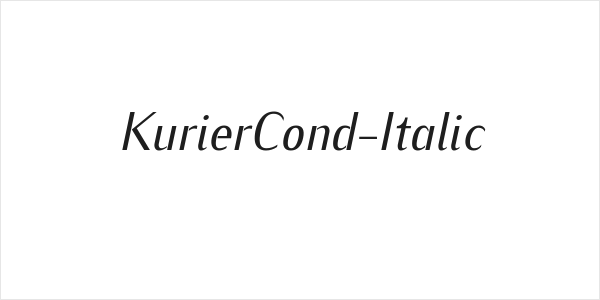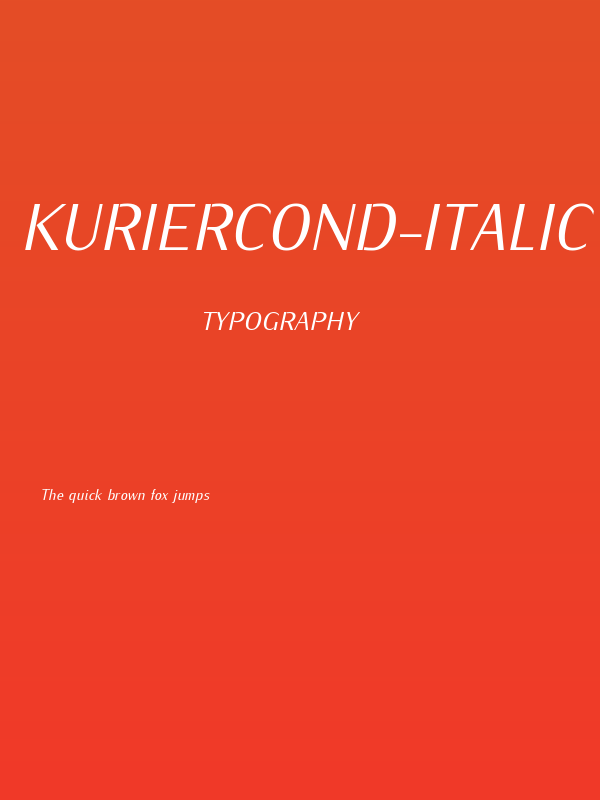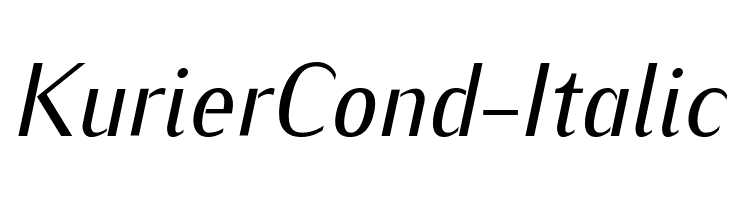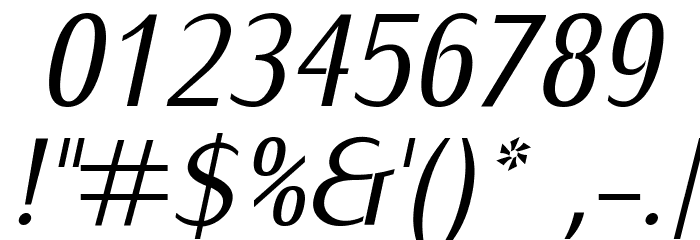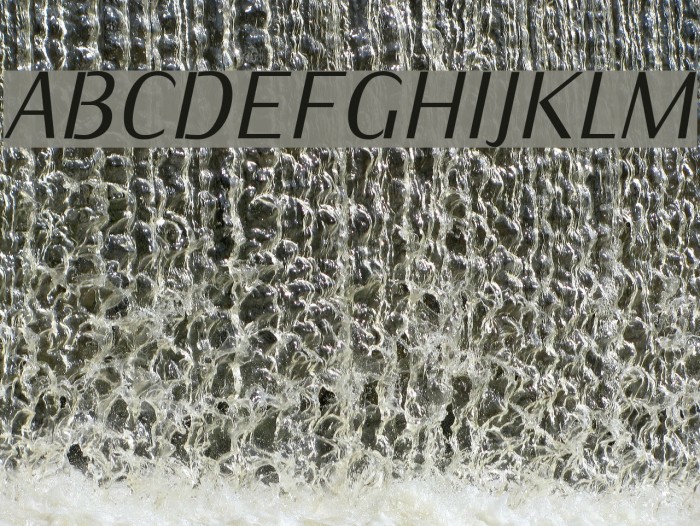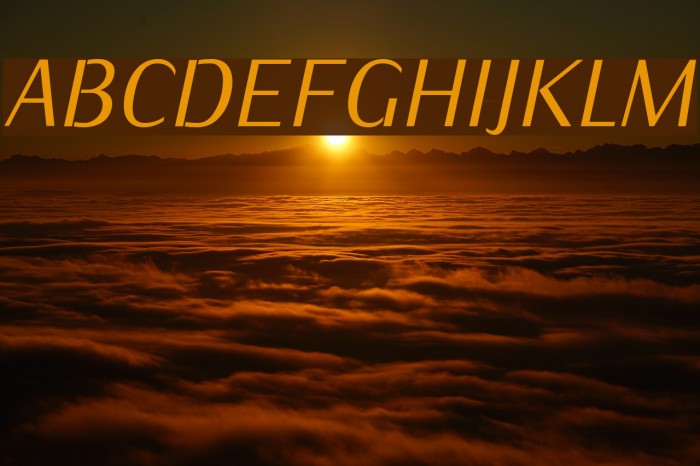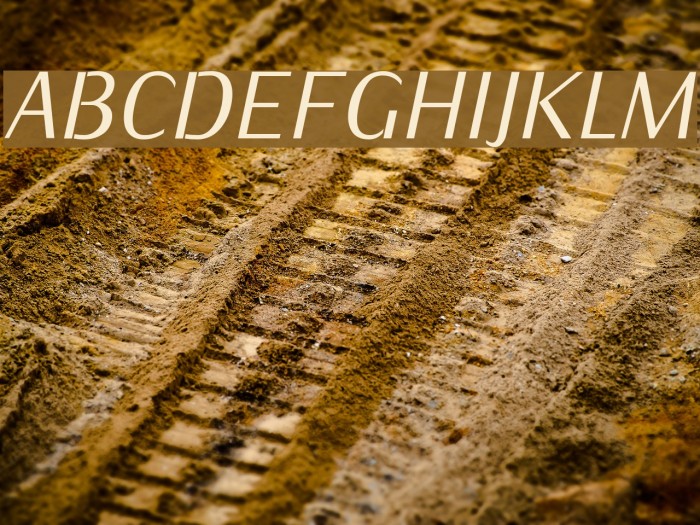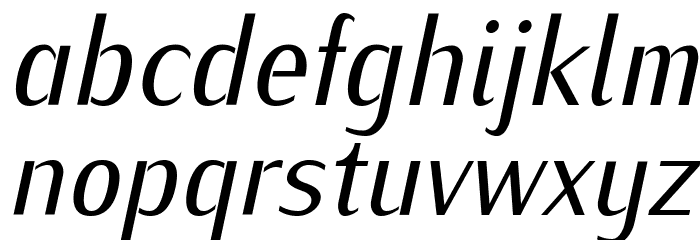
KurierCond-Italic Font
| Progetti proposti | Ideal for branding, editorial design, advertising, and digital media where a modern and sophisticated touch is desired. |